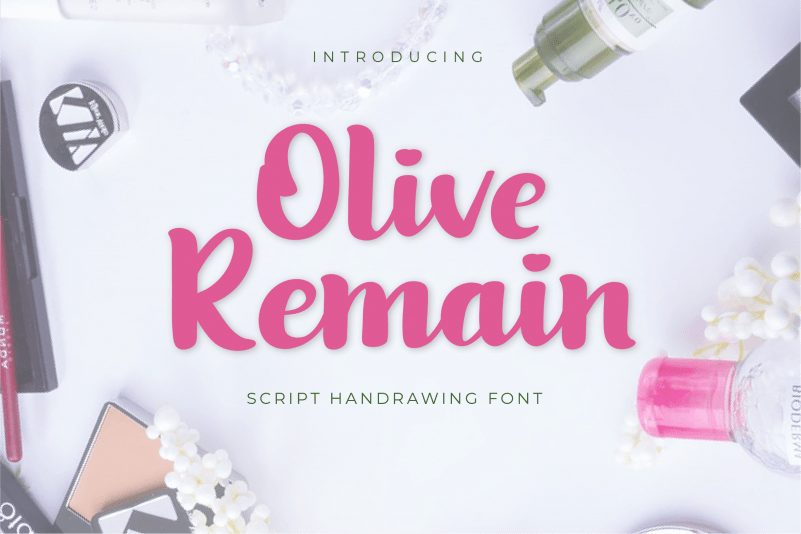
A Olive Remain Script Font é uma linda fonte tipográfica à mão escrita desenvolvida pelo designer twinletter. Essencialmente perfeita para criar mensagens poéticas e românticas, esta fonte traz um toque de caligrafia elegante que se encaixa perfeitamente em aplicativos como cartões personalizados ou e-mails. Uma das características mais apreciadas dessa fonte é seu estilo suave e fluido, projetado para deixar uma impressão única sobre qualquer projeto. Com sua liberação gratuita apenas para uso pessoal, esta é realmente uma fonte que todos devem experimentar, especialmente aqueles que buscam uma maneira de tornar seus textos ainda mais atraentes e singulares. Se você aprecia essa fonte e deseja usá-la em projetos comerciais, não hesite em fazer um pequeno doação para ajudar no desenvolvimento da designer. Se preferir pagar via PayPal, o link está disponível na descrição original da fonte.